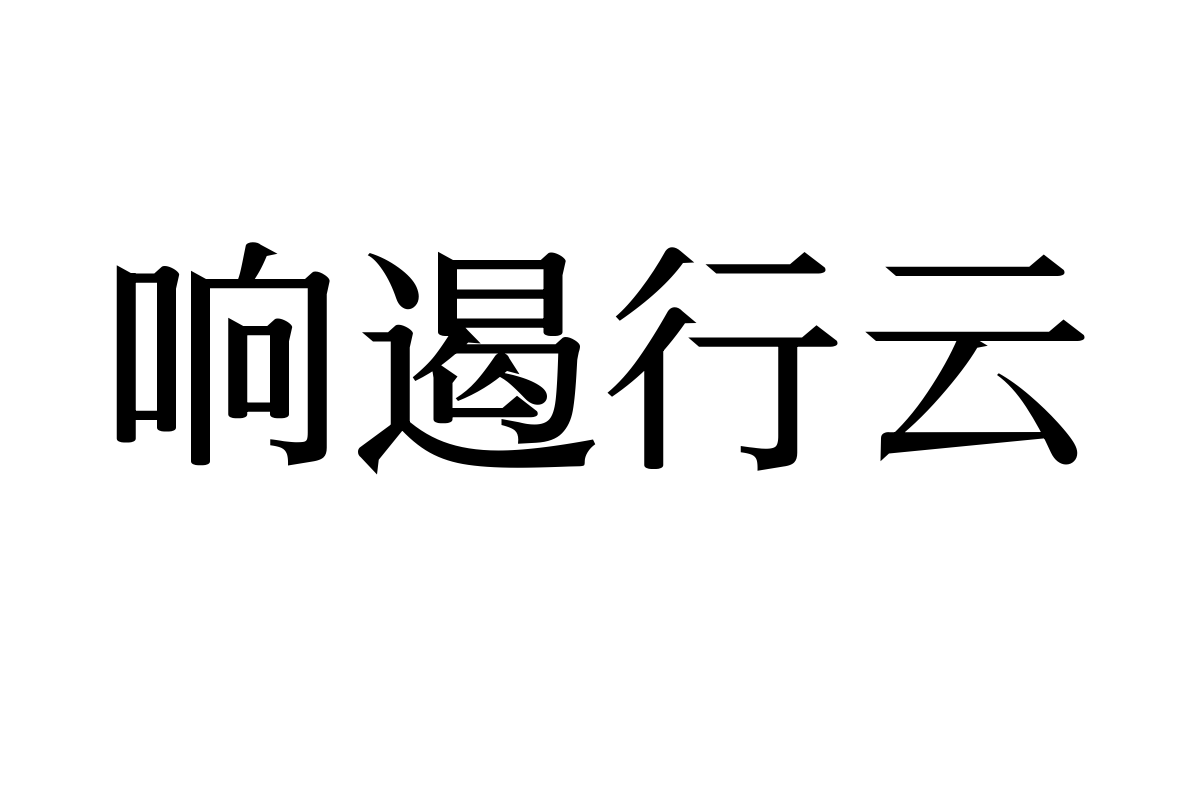
三极萧宋是一套由台湾设计师李明宗设计,以汉字书写为灵感的现代字体。它的特点是线条流畅、结构简洁、风格独特,具有很高的辨识度和艺术价值。
三极萧宋采用了大量的书法元素,如笔画的粗细变化、字形的倾斜角度等,使得字体具有强烈的视觉冲击力和艺术表现力。同时,它也注重平衡和对称,使得整体看起来既和谐又富有动感。
此外,三极萧宋还采用了一些现代设计手法,如简化的笔画、抽象的形状等,使得字体更加符合现代人的审美习惯。同时,它也具有一定的可读性,使得人们在阅读时能够轻松地识别和理解信息。
总的来说,三极萧宋是一种非常独特的现代字体,它既有传统的韵味,又不失现代感,是汉字书写艺术与现代设计相结合的产物。